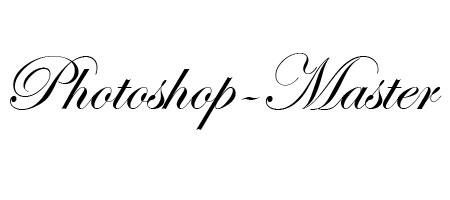
Красивый*-*
Спасибо, красивый шрифт. :)
Спасибо хороший шрифт
неплохо
Спасибо прикольный шрифт :)
спасибки!!! Прикольный шрифток!
Обожаю этот шрифт))))
отличный шрифт!!
Спасибо за такой прелестный шрифт))
подписывать открытки самое то!)
Класно
красивый шрифт